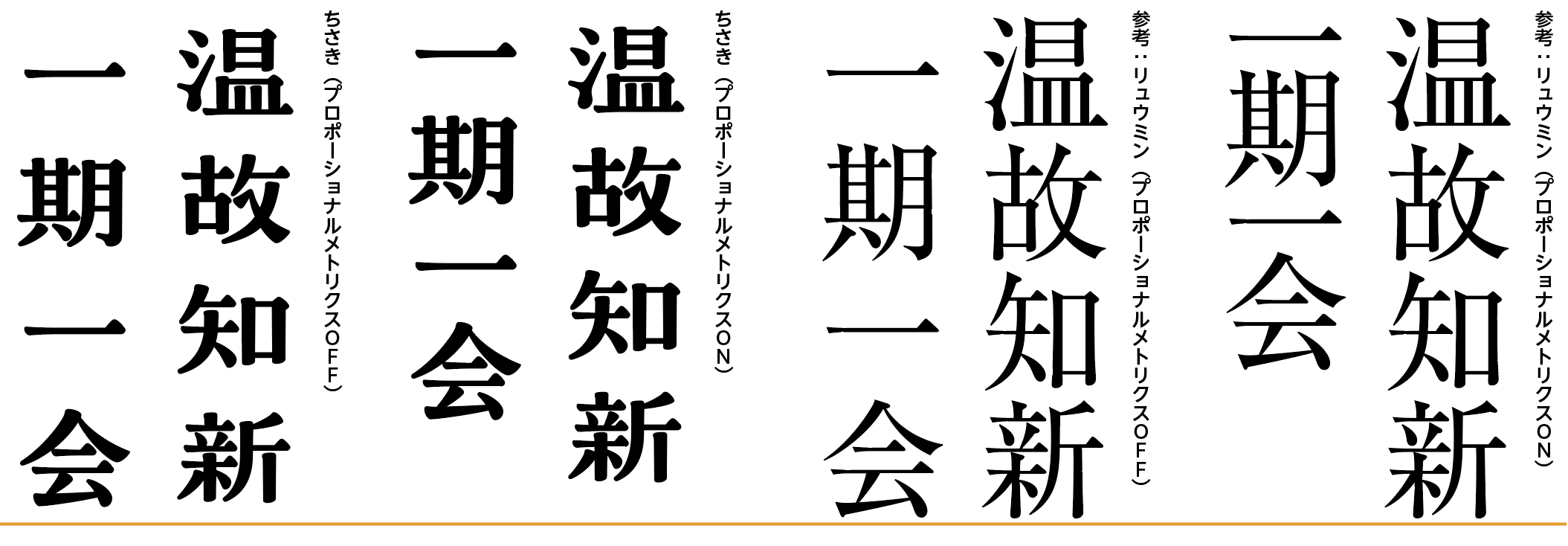
【ちさきの特徴】
ちさきは仮想ボディに対して平体の書体で、デフォルトの縦組みでは全角幅でゆったりと空間をとった文字送り、縦組みプロポーショナルメトリクスを有効にすることでそれぞれの文字の高さに沿った文字送りを行うことができます。
モリサワの一般的な和文書体とのちがい
モリサワの一般的な和文書体では、縦組みプロポーショナルメトリクスを有効にした場合一部の漢字や非漢字のみ固有幅、その他のグリフは全角での文字送りとなります。一方ちさきで縦組みプロポーショナルメトリクスを有効にした場合は、大半の漢字と一部の非漢字は全角の96%での文字送り、その他の縦組みプロポーショナルメトリクス対象グリフは固有幅 、その他のグリフは全角での文字送りとなります。
縦組みプロポーショナルメトリクスON/OFF比較
なお、横組みでプロポーショナルメトリクスを有効にした場合には、通常の書体同様に一部の漢字や非漢字のみ固有幅、残りのグリフは全角での文字送りとなります。
ペアカーニングを有効にするには
プロポーショナルメトリクスを有効にした際、ペアカーニングも合わせて有効にしていただくことでさらに最適な文字組が実現されます。
【縦組みプロポーショナルメトリクス字形一覧】
縦組みプロポーショナルメトリクスを有効にした際に96%幅での文字送りとなるグリフと、固有幅での文字送りとなるグリフの一覧は、それぞれ以下の通りです。どちらにも掲載のないグリフは縦組みプロポーショナルメトリクスを有効にした際も全角での文字送りとなります。
ちさき B 縦組みプロポーショナルメトリクス適用時文字送りが960幅のグリフ一覧
ちさき B 縦組みプロポーショナルメトリクス適用時文字送りが固有幅のグリフ一覧